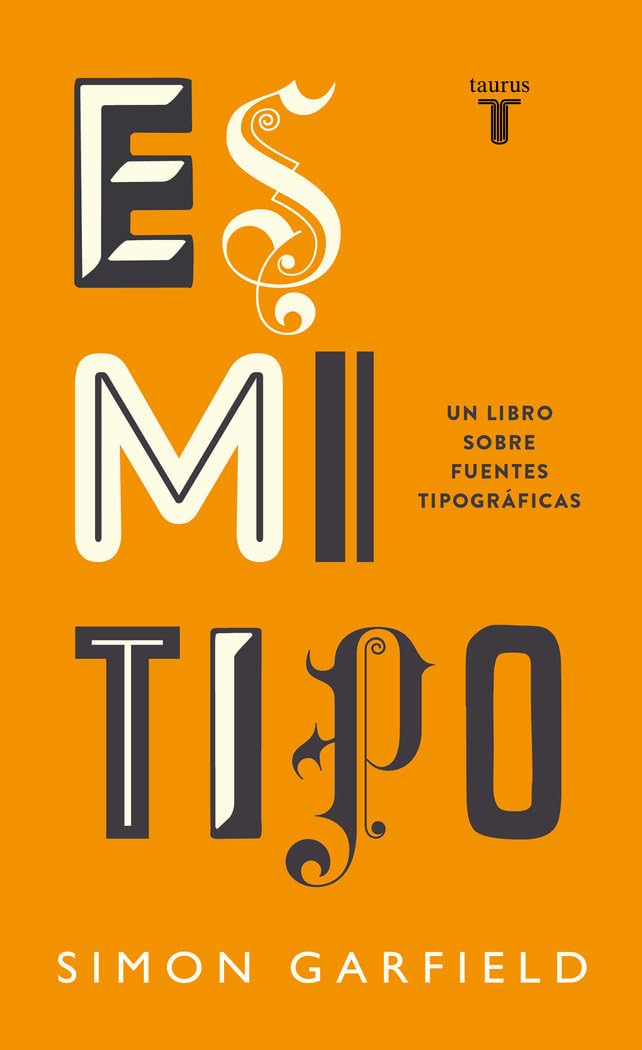
Detalles: ¿Cuál es tu tipo? Una desenfadada introducción al mundo de la tipografía.
Desde que las tipografías se mudaron a la barra de herramientas del ordenador todos comenzamos a tener una opinión sobre ellas. Hoy es imposible ignorar su poder, su omnipresencia en las marcas que nos rodean o el carácter que imprimen a nuestros textos. Y si no, ¿por qué despierta tantas antipatías el uso de Comic Sans? ¿A qué se debió el revuelo causado cuando Ikea fue infiel a Futura con Verdana? ¿Por qué Obama decidió optar por la Gotham como su distintivo gráfico? ¿Qué hace que una tipografía «funcione»?
Este divertido libro, profusamente ilustrado, cuenta la historia de más de doscientas fuentes desde su nacimiento -y en algunos casos hasta su muerte- a través de anécdotas sobre su empleo, sus creadores y sus usuarios. Garfield explica los fenómenos que hay detrás del dominio de fuentes como Helvética o Times New Roman o del odio hacia otras como Papyrus. Es mi tipo tiene todas las respuestas para quienes alguna vez se preguntaron qué tienen en común EasyJet y los Beach Boys, cuál es la tipografía favorita de Hollywood o si, como las personas, algunas fuentes son de Marte y otras son de Venus.